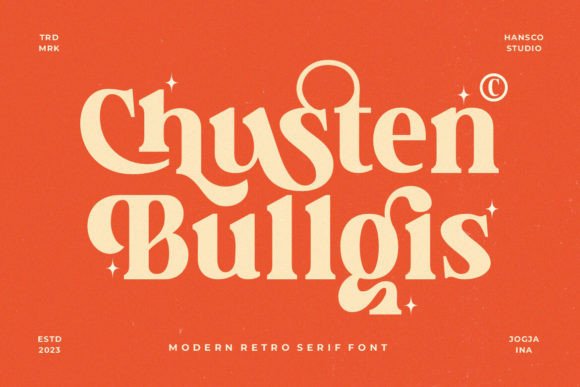
Chusten Bullgis
Se stai cercando risorse di alta qualità come Chusten Bullgis, questo pacchetto premium è una scelta fantastica per i tuoi progetti creativi.
Che tu stia creando prodotti POD (Print on Demand), partecipazioni di nozze o grafiche per i social media, Chusten Bullgis è la scelta ideale.